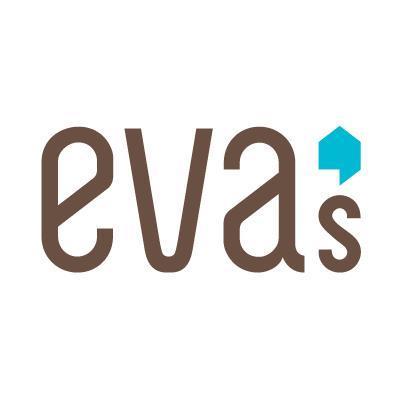
Welche Schrift ist das? (eva)
Hallo, ich finde diese gerade im Bezug auf den Namen "Eva" sehr schön.
Kann mir bitte jemand sagen, wie diese Schrift heißt.
willkommen im Forum. Ich würde mal stark davon ausgehen, dass die Buchstabenformen für das Logo gestaltet worden sind.
Auf der Website und in den Publikationen der Eva's Initiatives for Homeless Youth werden durchweg andere Schriftarten verwendet.
Hallo Martin, auszuschließen ist das natürlich nicht. Ich habe gerade die Schrift "SIMPLIFICA" gefunden. Die passt schon ziemlich gut, nur das "v" ist spitz.